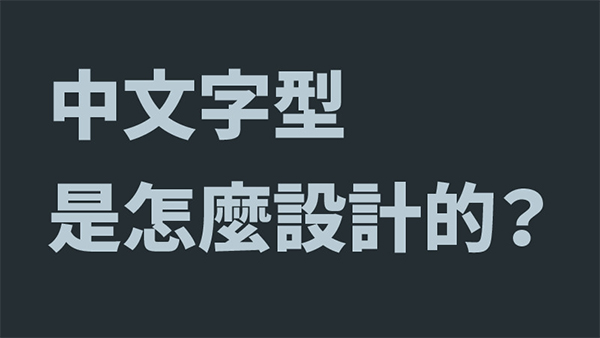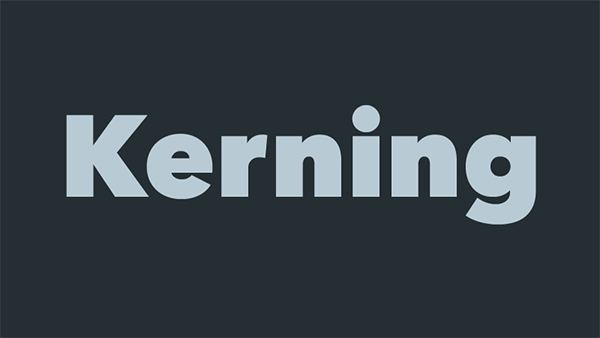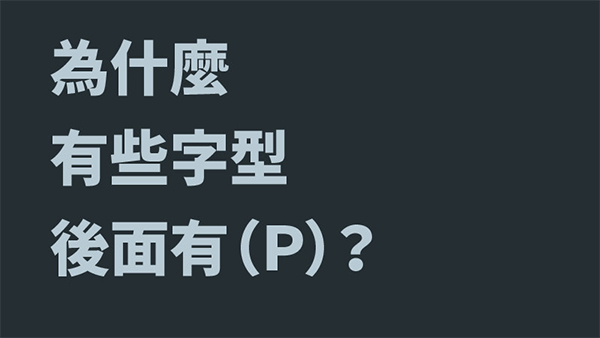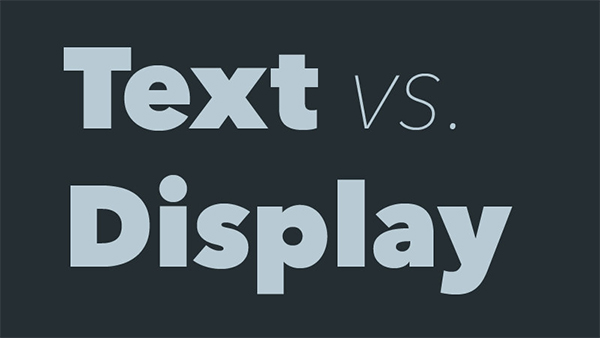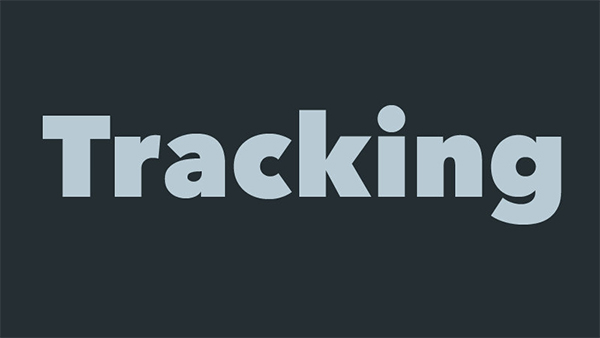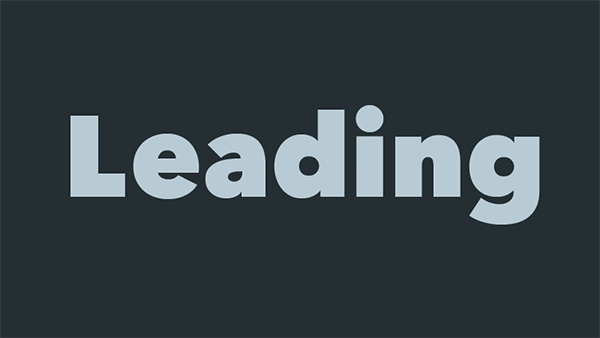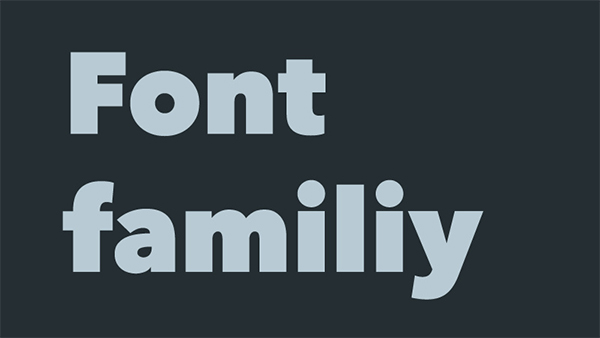
字型设计基础
在这两年推广字型的过程中,我们发现字型与版面编排其实是一把钥匙,打开视觉设计的大门。厉害的设计师对字体绝对不马虎,他们了解文字并不只是资讯的载体,在版面上也是视觉的元素。理解字型与版面编排,就等于掌握了视觉传达的核心概念。justfont 今年初上线的微型内容网站 jf tips 近两个月来开始推出「新手村」系列文章,从最基础的字型知识开始带设计初学者进入这个领域。我们在这里汇整、引荐其中八大主题给需要接触基本视觉设计的学者。
保持距离之必要:Kerning
Kerning 虽然是老梗,但无论怎么强调也不为过。不仅包含了好不好读也包含了好不好看。学习掌握空间的距离与比例关系,是学习学习视觉设计的第一步。Kerning 不止出现在英文,就连中文也有需要 Kern 的地方。其实,控制距离的功夫不管对哪一种语言来说都很重要。这也可以让我们了解到文字在版面上其实是图像的一环,不仅仅是表达资讯的载具而已。
说话的语气:Tracking
语气也能转化为排版样式。当文字距离比较开的时候,好像在慢慢说话,反之,则有一种紧迫的感觉。《字型之不思议》提到有些品牌之所以有高级感,很重要的因素是文字的间距展现了大人一般从容不迫的说话口吻;我们也发现很多潮牌,例如 Superdry,就喜欢压缩文字间距带来完全不同的感受。为什么只是文字距离的不同,就可以带来这么大的变化呢?
让文字呼吸:Leading
Typography 这门学问,很大一部份有关于空间的配置。行距是让文字呼吸的空间。它能让读者的眼睛认为文字有方向,而不是一坨黑黑的东西。这就是 Typography 一直很要求的 Readability(可读性)。但你知道行距是怎麽来的吗?不同的字体要设不一样的行距吗?看起来只是取个空间,但其中可是大有学问喔。
差一个字就不一样:字型 vs. 字体
字型跟字体有什麽不一样呢?为什麽我们有分清两者的必要呢?其实是这样的,人类很早以前就有字体,但是有字型还是很近代的事情。特别是能供个人任意选用的字型产品,更是最近三十年的事情呢。虽然在日常生活的沟通情境中,这两个字的意义与内涵可以是互通的,但是有基本的差异在。立志成为专业设计师的你,也要了解一下喔!
区隔得一团和气:字型家族
一团和气,但又各自独立,有这样的东西存在吗?有。字型家族就是这样的事情。这不是八点档剧名。它是 font family 的直译,一个非常有用的排版发明。成员都很独特,但又能相互搭配得家和万事兴。他们有相近的基因:骨架、装饰部分、气质等等,都很相近,只是粗度或样式的不同(样式指的是例如正体、斜体的不同)这样就能各司其职,又能合作无间。配备广大字型家族的产品也是挑选字型的一个面向,会让设计师省去许多搭配的麻烦。
藏在小细节里的重要知识:为什么有些字型后面有(P)?
这是一个看起来不重要,但其实背后大有玄机的东西,可以让我们学到关于欧文字型的重要知识。P 可不是随便乱取名的。它的意思是 Proportional,与 monospace 是相对概念。中文字型内建的欧文字型常常良莠不齐。字型厂商常常为同一套中文字型出产两种不同版本,一个是后面有 (P) 的版本,一个是普通的版本。它们的差异,其实不在中文,而在欧文英数上面。
各有各的长处:内文字型 vs. 展示字型
在众多字型产品里,可以分成两种:用于内文的「内文字型」与装饰性用途,通常用于标题等展示用途的「展示字型」。两种字体主要差别是什么呢?其实就是使用情境,内文字型用于长时间的阅读,讲究均值平稳的特性。要让读者埋首苦读数小时,仍然能沉浸其中,眼睛也还是很舒服的字型。展示字型不一样,通常因为是标题、招牌大小,字体比内文大数十、数百倍。它要能抓住目光,要醒目,而且最好要有味道。
都是设计师血汗的结晶:中文字型是怎么设计出来的
「字型」不是从电脑里喷出来的吗?的确有人问过这个问题。翻译成白话就是「字型不是电脑自己产生的吗?」当然不是。这样认为的话,字型设计师们情何以堪呢?字型这种东西,一笔一画都是工艺的心血结晶啊。不论是一笔一画的描绘,还是用笔画组件自动拼装成字型,字型设计都是很漫长的过程。上万个字要保持一致的品质,是最考验中文字型设计师的功夫。